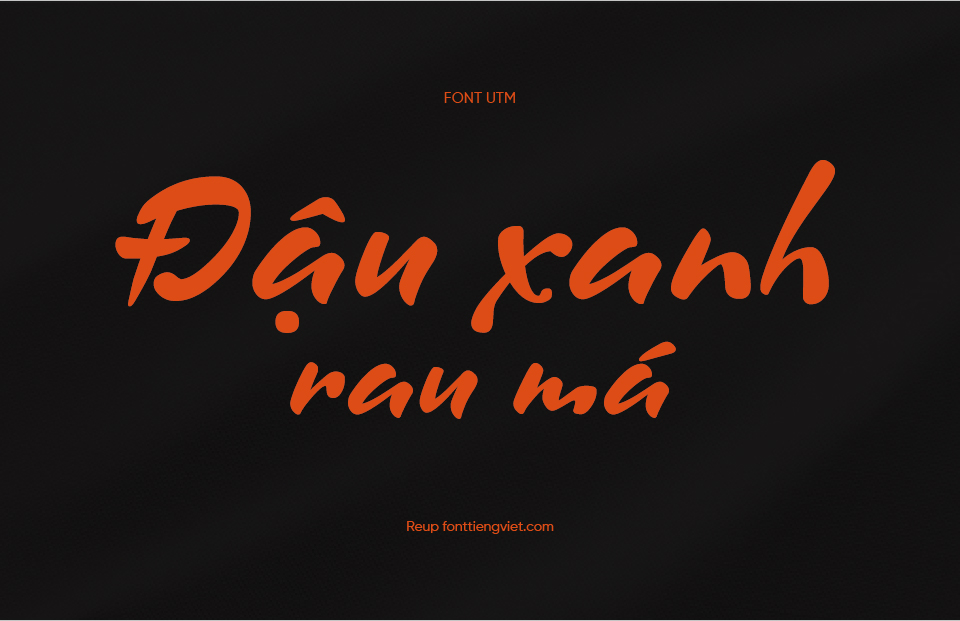
Font Việt hóa UTM Netmuc KT
Giới thiệu về bộ Font Việt hóa UTM Netmuc KT
Trong thế giới đồ họa hiện đại, việc tìm kiếm một bộ Font Miễn Phí chất lượng luôn là ưu tiên hàng đầu của các nhà thiết kế. Font Việt hóa UTM Netmuc KT nổi lên như một lựa chọn hoàn hảo nhờ phong cách thiết kế độc đáo và khả năng hiển thị tiếng Việt trọn vẹn. Bộ phông chữ này thuộc hệ thống UTM nổi tiếng, giúp người dùng dễ dàng truyền tải thông điệp một cách nghệ thuật nhất.
Đặc điểm nổi bật của Font Việt hóa UTM Netmuc KT
Đặc trưng lớn nhất của Font Việt hóa UTM Netmuc KT chính là những đường nét thanh mảnh nhưng vô cùng sắc sảo. Nó không chỉ đơn thuần là một công cụ gõ văn bản mà còn là linh hồn cho các tác phẩm thiết kế từ poster, banner quảng cáo đến các thiệp mời sự kiện. Sự tinh tế trong từng nét chữ giúp tạo nên sự chuyên nghiệp và thu hút thị giác mạnh mẽ cho người xem.
Cách ứng dụng Font Việt hóa UTM Netmuc KT trong thực tế
Sáng tạo nội dung số và in ấn
Nhờ tính ứng dụng cao, Font Việt hóa UTM Netmuc KT được sử dụng rộng rãi trong cả lĩnh vực in ấn truyền thống và truyền thông kỹ thuật số. Bạn có thể dùng nó để làm tiêu đề cho các bài viết trên mạng xã hội hoặc thiết kế bìa sách giáo khoa. Phông chữ này giúp các em học sinh và giáo viên dễ dàng tiếp cận thông tin một cách trực quan và sinh động hơn bao giờ hết.
Kết luận và tải xuống Font Việt hóa UTM Netmuc KT